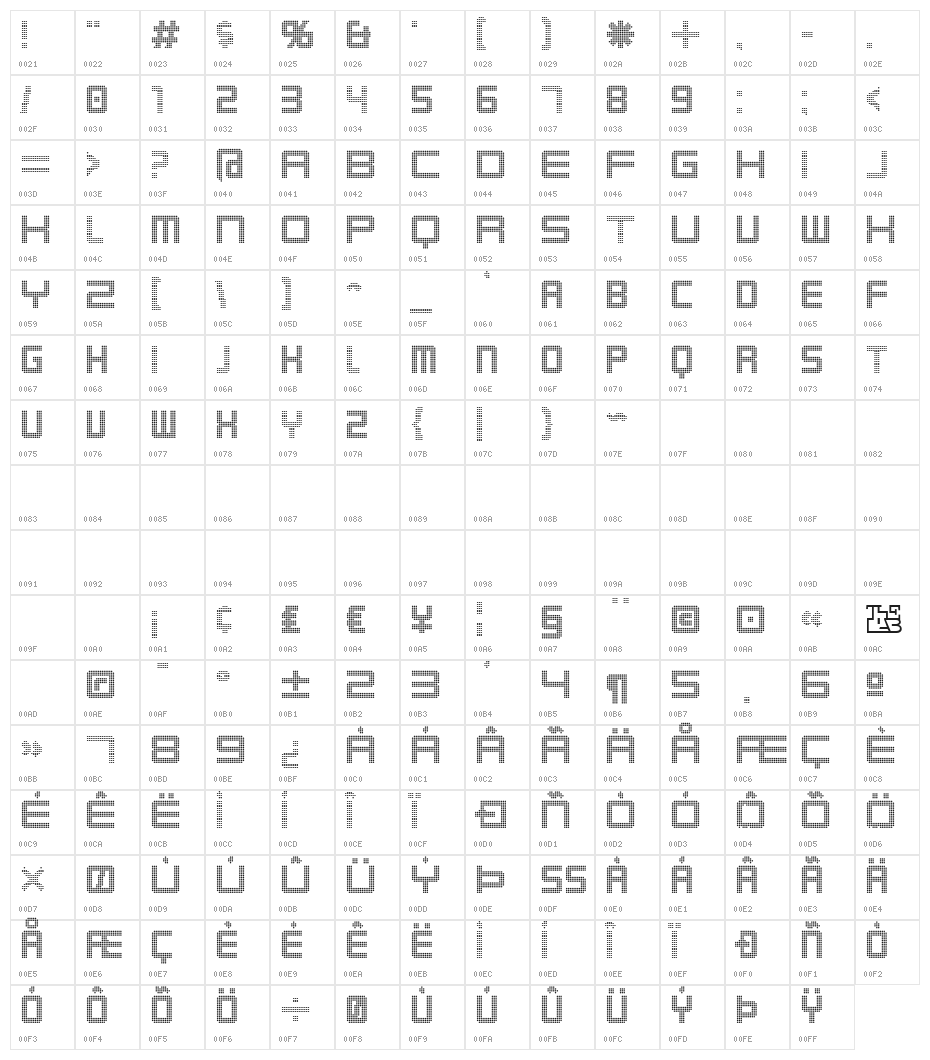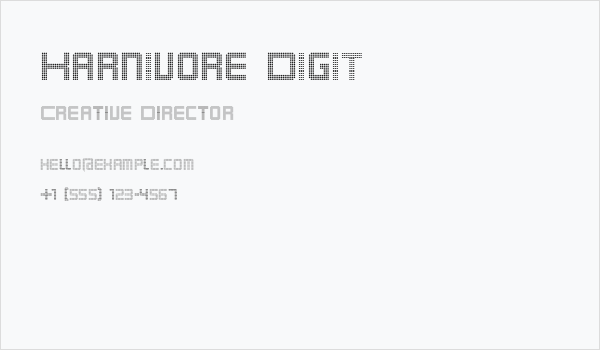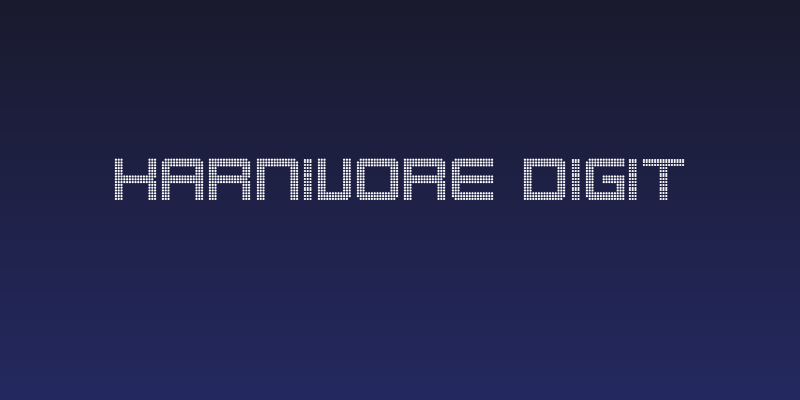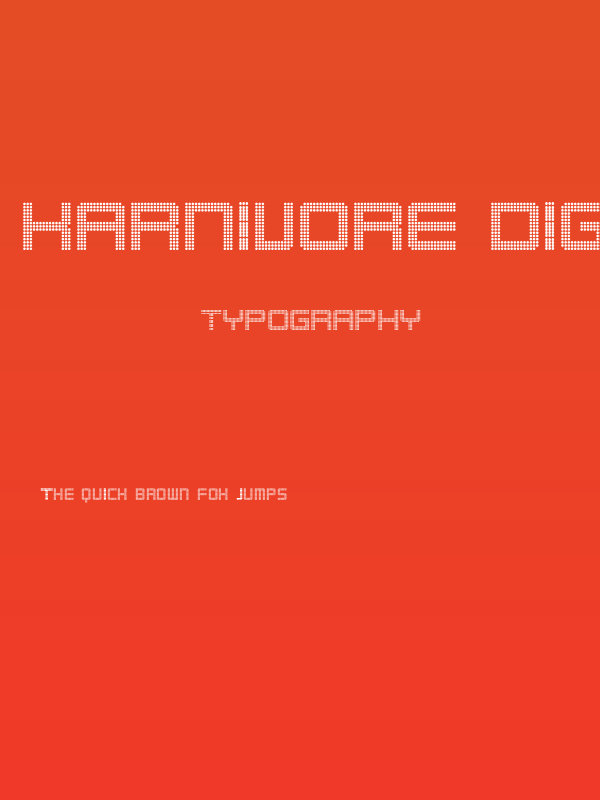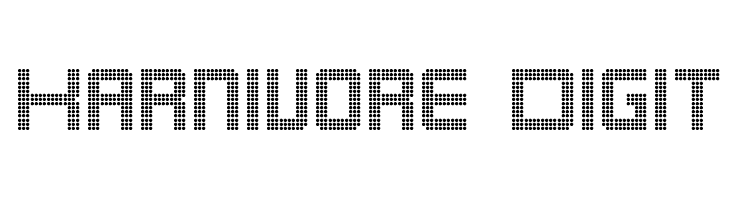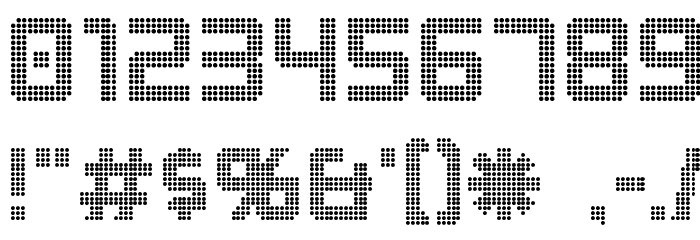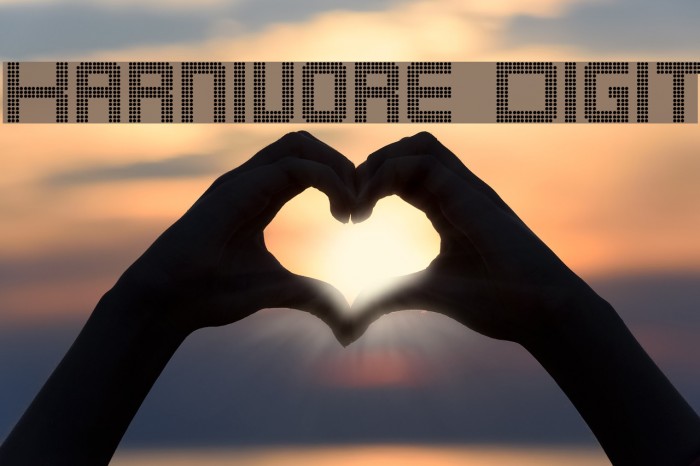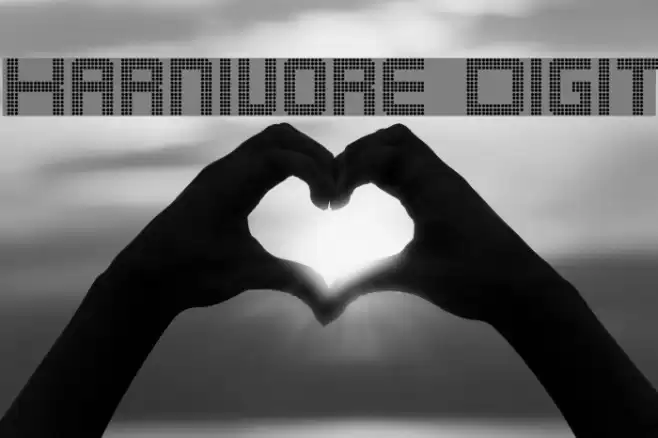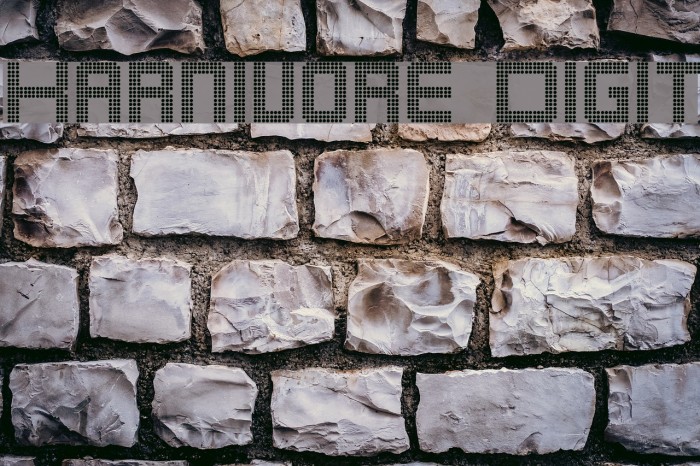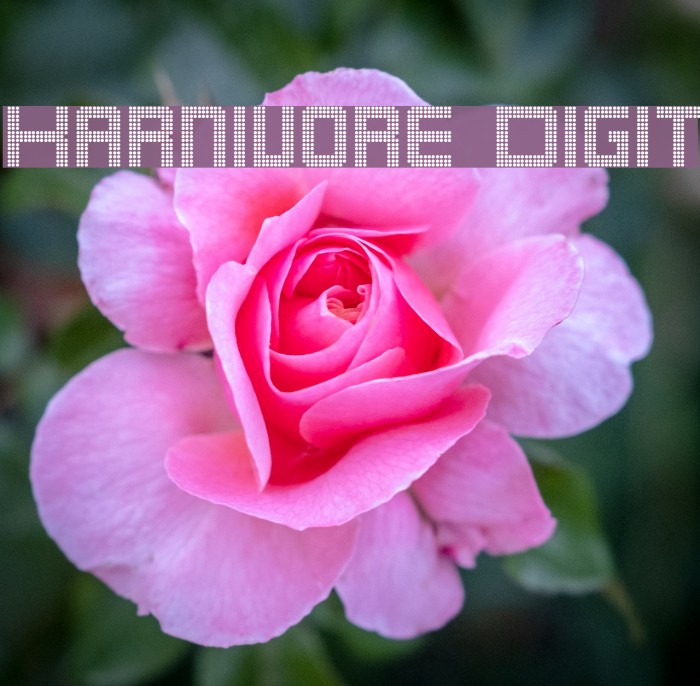
Karnivore Digit Font
✎ Pixel
| Kategorien | Pixel |
| Anwendungsfall | Headlines, Logos, Digital Displays |
| Vorgeschlagene Projekte | Ideal for digital displays, tech-themed posters, retro video game graphics, and modern digital art. |